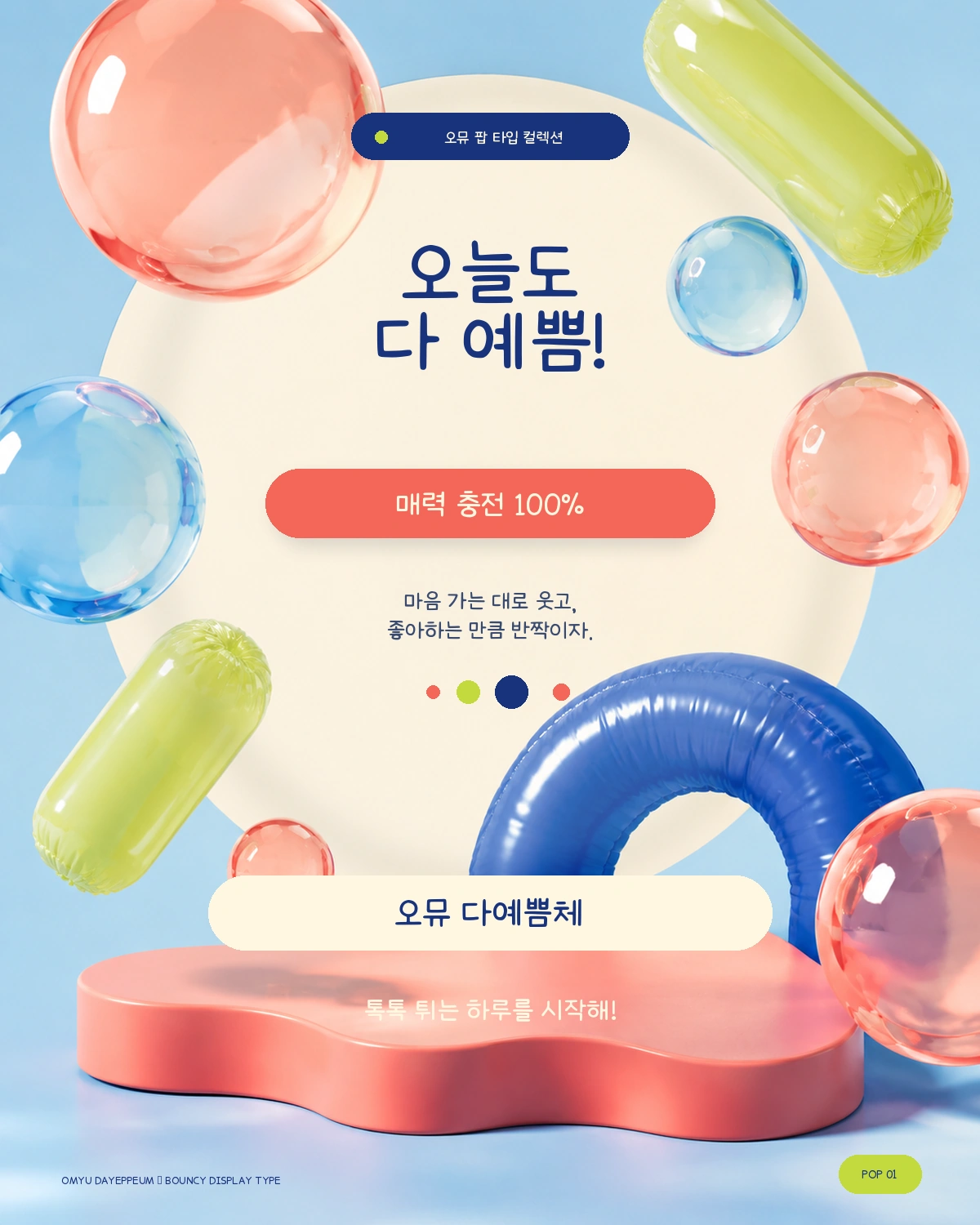
오뮤 다예쁨체 — 오뮤다이어리 x 보이저엑스에서 배포하는 무료 폰트입니다. 무심한 듯 반듯하게 정리한 획으로, 태블릿에 직접 쓰는 대신 타이핑으로 손글씨 느낌을 내는 서체
굿노트용 디지털 다이어리와 스티커를 만드는 오뮤다이어리가 보이저엑스와 함께 만든 손글씨 서체입니다.
제작사가 쓴 소개가 이 서체를 누구에게 권하는지 분명히 밝힙니다. 미끌한 액정에 펜을 잡는 게 어색한 분, 손글씨를 쓰기엔 효율이 더 중요한 당신을 위해 무심한 듯 반듯한 서체가 도움이 되길 바란다는 것입니다. 태블릿에 직접 손글씨를 쓰는 대신 타이핑으로 그 느낌을 내려는 사람을 겨냥했다는 뜻입니다.
파일에서 재어 보면 받침 유무에 따른 높이 차가 거의 없는 네모틀이라 글줄이 가지런합니다. 굵기는 하나이고 현대 한글 11,172자를 모두 담았습니다. 라이선스에 눈여겨볼 조항이 있습니다. 인쇄와 웹, 영상, 판매용 제품, 임베딩, BI와 CI까지 쓸 수 있지만 폰트를 고칠 수 없고 재배포와 유료 판매가 금지되며, **손글씨 관련 제품은 판매할 수 없습니다.** 캘리그래피 교재나 굿즈를 만드실 계획이라면 미리 확인하세요.